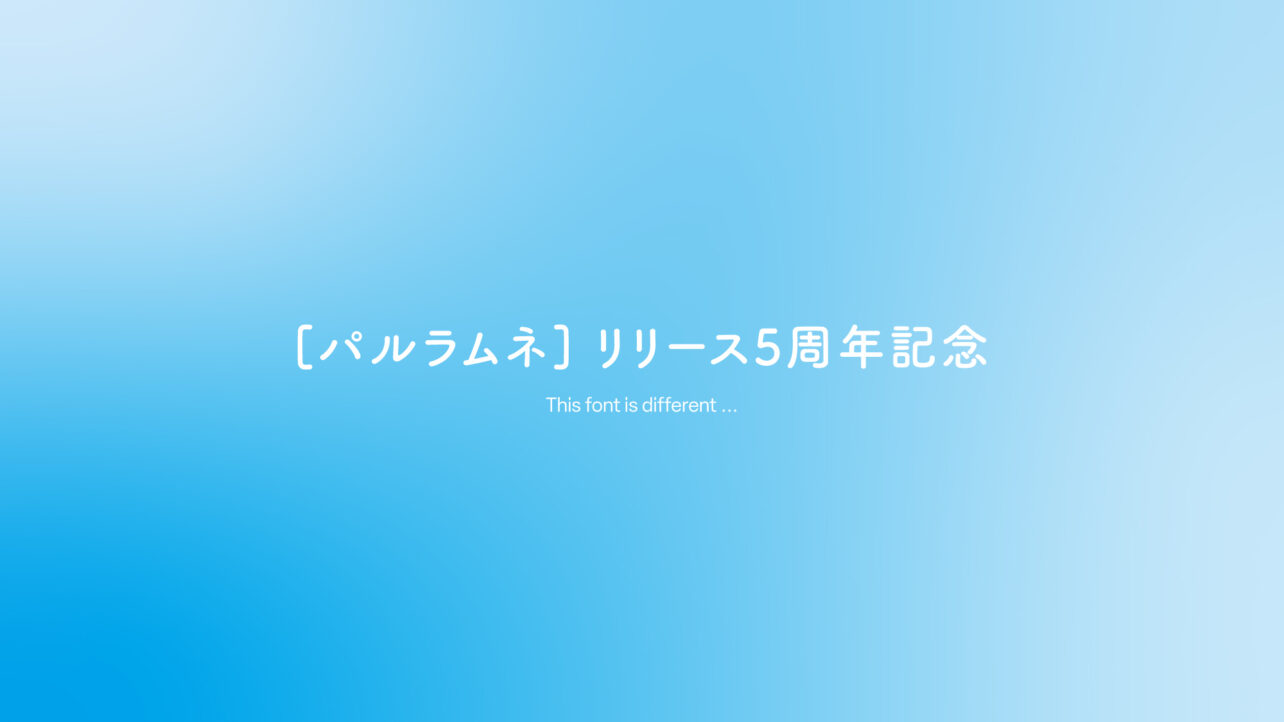
人気フォント[パルラムネ]リリース5周年記念。イラストレーター かとうれい氏による書き下ろしイラストのスペシャルサイト公開
フォントワークス株式会社は、2017年に登場し今年で5周年を迎えた書体『パルラムネ』のスペシャルサイトを公開した。
書体紹介『パルラムネ』
フォントワークスの書体デザイナー・越智亜紀子が制作。2017年のリリースから今年で5周年を迎え、フォントワークスを代表する書体の1つとなった。ゆるい雰囲気にあどけない愛らしさを醸し出す書体で、漢字と仮名で異なるサイズの凸凹感が、文字を組んだ際にリズミカルな表現になる。軽やかに跳ねたテンとハライが特徴で、タイトルやキャッチコピーを活き活きとさせる。
使用事例
多くの皆さまに愛される書体となり、テレビ・書籍・食品パッケージなど幅広い分野で使用されている。
越智亜紀子 プロフィール
日本大学芸術学部デザイン学科卒業。2012年フォントワークス株式会社入社。日々の書体制作で基本を学びつつ、キャッチ・ポップ系をデザイン担当。2017年最初の書体『パルラムネ』をリリース、2019年にはパルシリーズの第2弾となる「パルレトロン」をリリース。現在『パルもこ』などパルシリーズを順次開発中。
リリース5周年記念 「目と耳で文字を楽しむ」スペシャルサイト オープン
『パルラムネ』の魅力をもっと知れるスペシャルサイトがオープンした。人気イラストレーター・かとうれい氏による書き下ろしイラストとともに、目と耳で『パルラムネ』の世界観を感じられる。サイト内では、越智へのインタビューも掲載。
「パルラムネ」スペシャルサイト